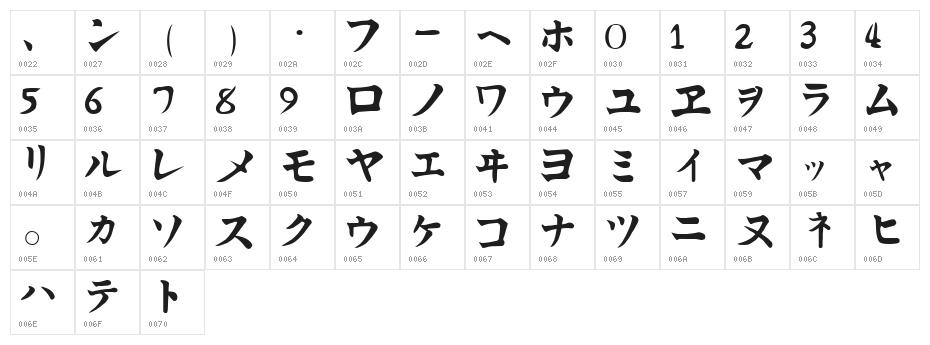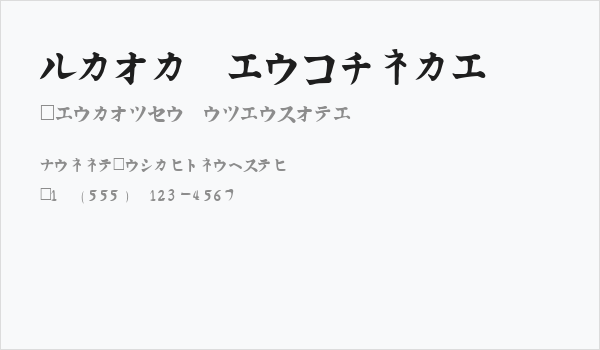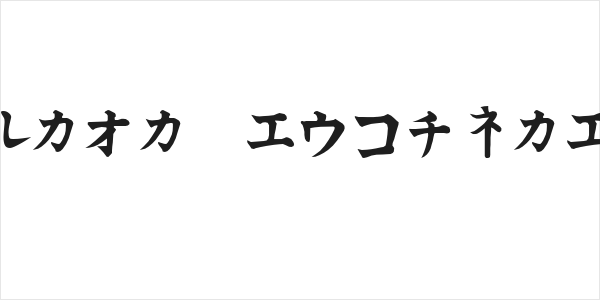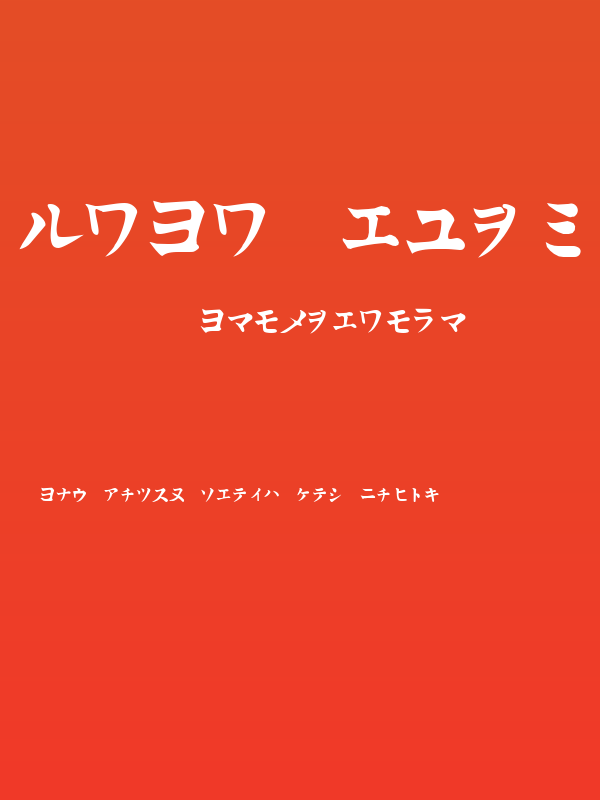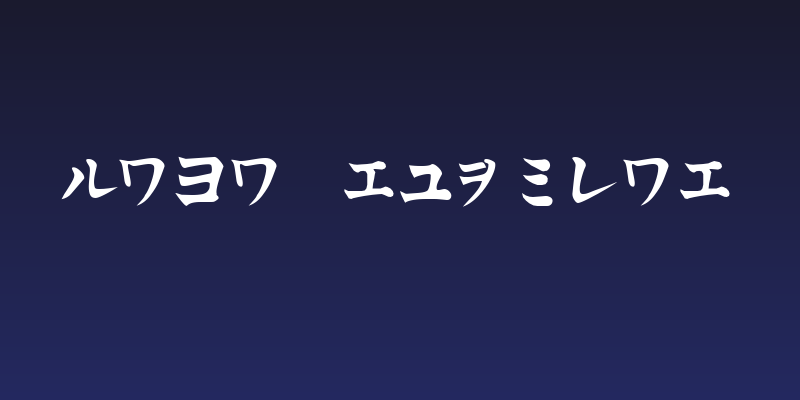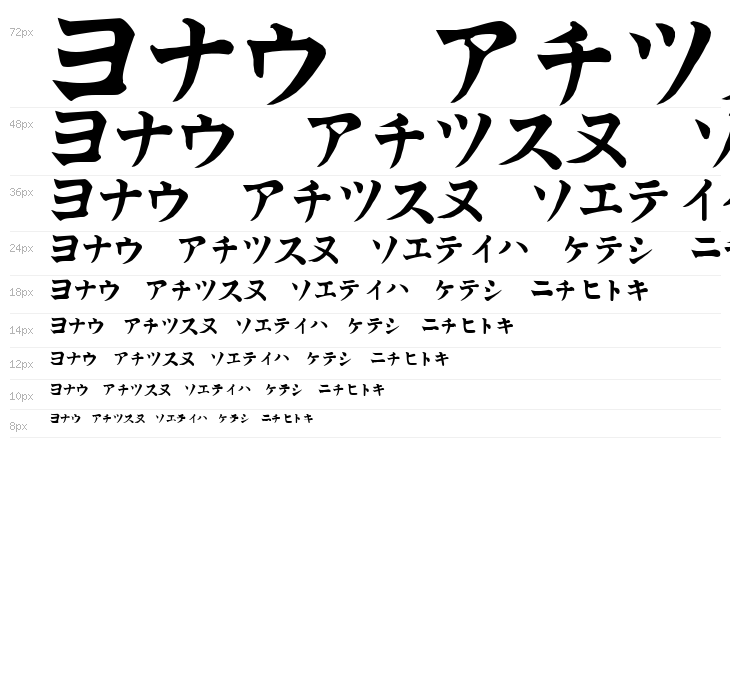
Kata Regular Font
| Caso d'uso | Logos, Invitations, Artistic projects |
| Progetti proposti | Ideal for cultural projects, artistic designs, invitations, and branding that seeks an authentic and expressive touch. |